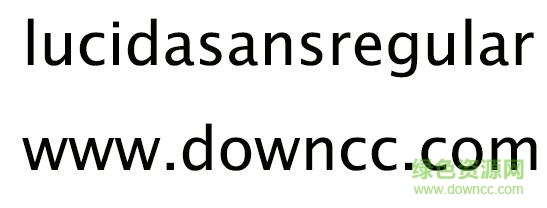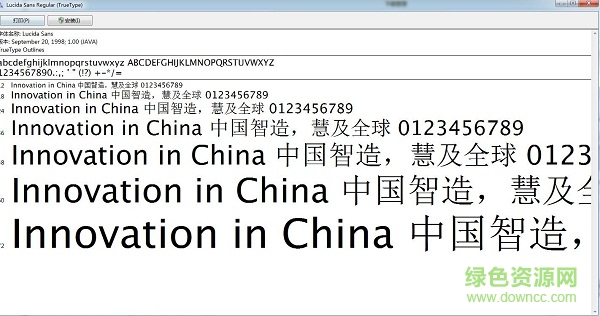
軟件介紹 軟件標簽: lucida字體 英文字體 lucidasansregular是什么字體?lucidasansregular.ttf刪除不了?這是一款很多電腦軟件自帶的英文無襯線字體,適合用在排版打印方面,期刊書籍等方面,有需要者歡迎免費下載!lucida字體推薦lucida family 字體 授權(quán):免費軟件 WinAll, WinXP, Win7大小:1010KB語言:中文lucida系列字體是小編專為廣大字體迷整理的lucidafamily字體合集,包含了lucidaconsole、lucidagrande、lucidasans、lucidahandwringe等所有常用的lucida字體,需要的朋友歡迎在綠色資源網(wǎng)下載!字體如何幫助信息傳下載地址lucida calligraphy italic 授權(quán):免費軟件 WinAll, WinXP, Win7大?。?6KB語言:中文lucidacalligraphy字體是一款筆畫修長的英文字體,字體線條隨意,字形秀美,整體看上去精美又大方,不論是用在廣告宣傳或是雜志海報上效果都非常好!字體涵義1.文字的外在形式特征。就是文字的風格,是文字的外衣。字下載地址現(xiàn)代字體特征1.筆畫對比及其強烈;2.鏈接襯線和字干的字弧被全部去除;3.小寫字母中的襯線變得非常圓滑。lucidasansregular字體安裝方法1.需要進行字體安裝方可調(diào)用字體2.將字體拖動到C:\Windows\Fonts文件夾進行安裝3.如若編輯器內(nèi)未顯示字體文件,可重新打開編輯器查看 軟件截圖 上一張下一張(1 / 1) 安裝詳細截圖 其他版本下載 標題 大小 更新日期 下載 下載地址 電腦版 lucidasansregular字體 點擊報錯 軟件無法下載或下載后無法使用,請點擊報錯,謝謝! 關(guān)閉報錯反饋 請描述您所遇到的錯誤,我們將盡快予以修正,謝謝! *必填項,請輸入內(nèi)容 本類最新 sounso beauty字體 spyced哥特英文字體 ttf版 zerodegrees字體 the next font ttf版 coolvetica font keep calm ttf 免費版 相關(guān)文章 我叫mt4哪個職業(yè)輸出最高 我叫mt4輸出最高的職業(yè)排行 非人學園哪個英雄厲害 非人學園最強英雄排行推薦 每個ASP程序員必備的知識 ASP.NET開發(fā)必須養(yǎng)成的編程習慣 ASP.NET兩個截取字符串的實用方法技巧 ASP:一個網(wǎng)站空間多個域名訪問 用戶評論 熱門評論 最新評論 發(fā)表評論 查看所有評論(0) 昵稱: 請不要評論無意義或臟話,我們所有評論會有人工審核. 字數(shù): 0/500 (您的評論需要經(jīng)過審核才能顯示)